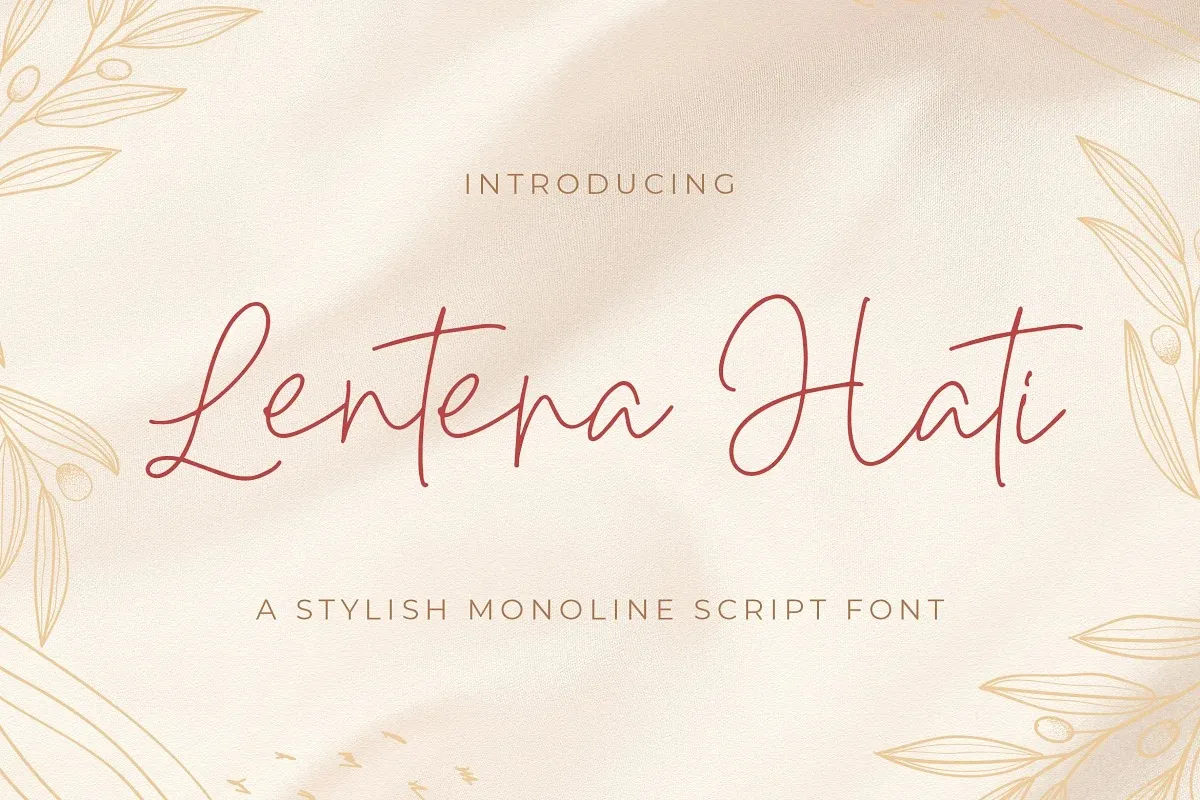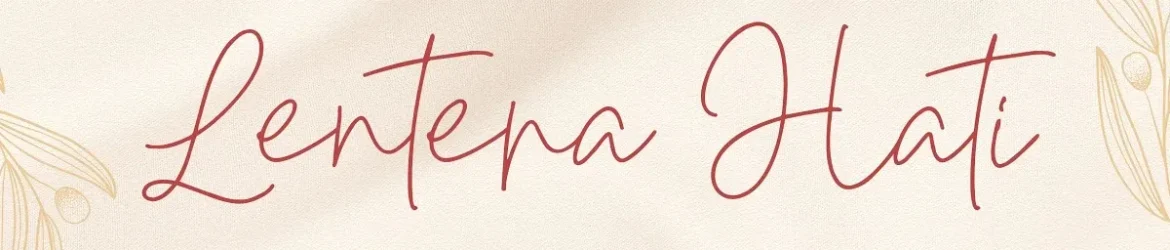
A Lentera Hati Font é uma elegante escolha para aqueles buscando uma fonte que exalte sofisticação e delicadeza. Esta fonte script fina e minimalista transpira elegância, ideal tanto para projetos profissionais quanto para ideias criativas de design pessoal. Desenvolvida pela StringLabs, a Lentera Hati é perfeita tanto em textos menores quanto grandes títulos, proporcionando uma ótima composição que se harmoniza com um vasto leque de estilos e temáticas. Experimente incorporar essa fonte à sua próxima criação — você não vai conseguir parar de notar como ela dá vida a suas ideias mais visionárias.